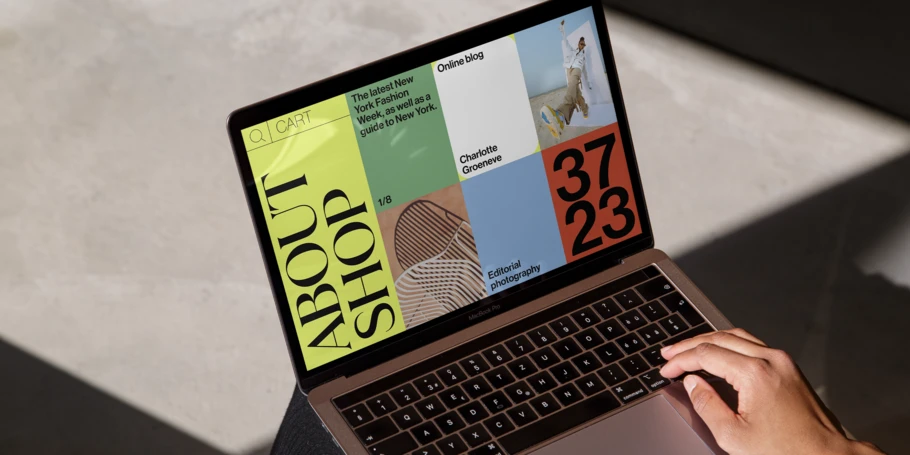
Expérience utilisateur : les nouvelles attentes des consommateurs et l’impact pour le design et la typographie.
“ Aujourd’hui, les consommateurs se comportent différemment. Ils attendent davantage de la part des marques. ”
Au cas où vous seriez passé à côté : le monde et la culture ont connu de grands changements ces derniers temps ! Au risque de tout mettre sur le dos de la COVID, la pandémie mondiale a généré un sentiment durable d’isolement et une forte dépendance à l’expérience digitale.
De son côté, le changement climatique a renforcé l’intérêt des consommateurs pour la biodiversité et la durabilité. Pour finir, les brutalités policières ont déclenché des mouvements de défense des droits civiques. L’attention des marques s’est alors portée sur les initiatives et l’activisme en faveur de la diversité, l’équité et l’inclusion. Découvrez comment ces changements influencent les attentes des consommateurs en matière de design, d’expérience utilisateur et de relation vis-à-vis de votre marque.
Les attentes numériques transformées par la pandémie
Entre les confinements, les apéros Zoom et le recours en masse au télétravail, il va sans dire que le temps passé chez soi et l’exposition aux écrans a connu une envolée considérable ces dernières années. Nous nous sommes attachés à des appareils rectangulaires de toutes sortes et de toutes dimensions. Nos actions virtuelles sont devenues nos seules interactions de la journée.
Pour beaucoup, communiquer avec les marques par voie numérique est devenu un confort non négligeable. Avant la pandémie, la communication avec une marque par message était la cinquième option parmi les canaux utilisés traditionnellement dans le cadre du service à la clientèle. Aujourd’hui, elle se hisse à la deuxième place. En conséquence, les marques les plus avisées ont abandonné leur posture froide et distante. Elles ont cherché des solutions pour entrer en contact avec leurs clients et faire preuve d’empathie, de solidarité.
Cet évènement a provoqué un effet « domino ». Les entreprises se sont unies aux luttes quotidiennes du monde, en apportant un côté plus doux à leur communication  et plus tendre à leur design. Pour la première fois, les « consommateurs ordinaires » externes à la communauté du design, ont commencé à percevoir l’aspect normé des espaces numériques, où les informations reprennent les mêmes modèles, les mêmes formules, les mêmes polices de caractères. Les responsables de marque et les créatifs ont pris conscience du manque de variété, de distinction et d’humanité face à l’abondance de nos objets numériques.
La pandémie comme accélérateur d’innovation pour les marques
Avant la pandémie, rares étaient les marques qui proposaient une réelle « expérience numérique » et leurs interfaces se résumaient à peu près à une seule chose : l’apparence. Pourtant, le facteur d’interaction est un des atouts majeurs du numérique : la façon dont nous déplaçons notre souris, notre réaction face aux menus et aux animations, et nos réponses aux questions.
En commençant à y accorder de l’importance, les marques ont finalement apporté davantage de nuance et de personnalité à leurs voix. Dans le design, la mise en place de polices variables, et la manière dont elles s’adaptent à tous types de scénarios en est un parfait exemple.
Le travail à domicile mène-t-il à une plus grande productivité ? C’est une question qui reste à déterminer. Mais force est de constater que l’économie des trajets et du temps passé habituellement au bureau, a rendu de nombreuses personnes ultras efficaces. En conséquence, leurs attentes concernant l’expérience utilisateur en termes de réactivité, voire d’instantanéité, ont également été décuplées.
Dans un élan de rapidité, les consommateurs sont prêts à prendre plus de risques. Par exemple, ils choisissent de se faire livrer plutôt que d’aller faire eux-mêmes leurs achats en magasin, au profit de la sécurité que leur garantit le déplacement sur place, d’un point de vue financier. En réponse à cette tendance, les entreprises ont dû réévaluer leurs mesures de personnalisation, de confidentialité et de sécurité. Si les polices variables ont encore un véritable potentiel, elles permettent aux marques de s’exprimer à l’aide de plusieurs voix et de proposer une expérience utilisateur plus ciblée.
Vers un désir collectif de divertissement et d’évasion
En l’espace de deux ans, le shopping en ligne a connu une réelle transformation. Nous sommes passés du simple achat sur des sites de e-commerce à des essayages de vêtements sous forme numérique, via des magasins virtuels. Le sentiment d’anxiété, l’isolement et  l’accentuation du temps passé à la maison ont renforcé le besoin de confort des consommateurs, vis-à-vis des nouvelles technologies et des expériences virtuelles.
Vous voulez une preuve ? Le métavers. Il suffit de se pencher sur l’exploration créative et les nombreux investissements dans ce domaine. Les frontières entre le réel et le virtuel évoluent. Pour cette raison, les marques doivent créer des expériences dignes de leurs promesses dans ces espaces :
• Selon les rumeurs, Apple devrait lancer ​un dispositif de réalité mixte au printemps 2023.
Le point commun de tous ces marqueurs de réussite ? Des choix typographiques bien pensés pour la création de la marque ou des campagnes publicitaires. Que vous choisissiez une police dans une bibliothèque, que vous modifiez une police existante ou que vous commandiez une police personnalisée, assurez-vous qu’elle représente avec justesse le message que vous souhaitez véhiculer et qu’elle soit à la hauteur de votre ambition technique.